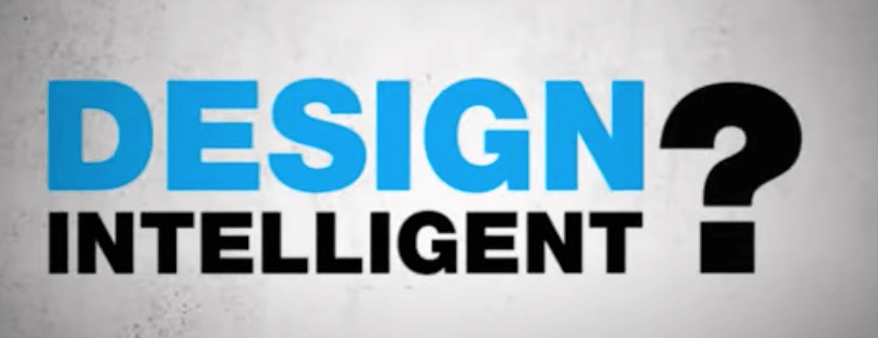
Dynamiser son design avec de la Typographie Animée
La Typographie : Place à l’animation et au Motion Design !
Voici le 4eme numéro de notre dossier sur la typographie, on commence à avoir vu en grande partie ce qui compose une police. Mais il nous reste maintenant à s'intéresser à son utilisation en animation, dans des clips, teasers, etc.
La Typographie en animation
On sait que la typographie fait partie intégrante de tout projet créatif qu’il soit un logotype, une affiche, un visuel, un site internet mais également une vidéo ou une animation. Dans cette article nous allons essayer de faire un tour rapide sur son utilisation dans les teasers, clips musicaux, sur les sites web, mais également dans des livres ! Commençons tout de suite avec ce qu’on peut appeler le Motion Typo que l’on voit depuis plus de 2 ans envahir les animations du web.
Le Motion Typo
En quelques mots je dirais que c’est l’art de créer une animation, avec comme seul élément principal "la typographie", ensuite c’est un jeu de mouvements, de compositions et de constructions avec les caractères. Voici quelques exemples pour illustrer.
La déclaration des droits de l’homme
Une animation reprenant la déclaration des droits de l’homme en vidéo conçue par Seth Brau et produit par Amy Poncher, on parcourt les différents plans entre illustrations et typographies sur une musique de Rumspringa.
Intelligent Design
Petite animation bien réalisée qui explique comment créer un design réfléchi et qui fonctionne, réalisé par Chrisitian Bramsiepe.
La typographie dans les Clips de musique !
Poursuivons notre dossier sur son utilisation dans les clips de musique, qui amène une dose de créativité et d’expérimentation pour le plus grand plaisir des yeux et des oreilles aussi ^^
Softlightes "Heart Made Of Sound"
Dans les teasers ou annonces d’évènements  !
Il parrait logique d’utiliser la typographie pour présenter des teasers où une grande partie de la vidéo, d’informer sur le sujet et de présenter l’évènement…Une petite liste d’exemples pour illustrer tout ça.
Join the Cannes Young Lions 48 Hour Ad Contest
La vidéo présente une compétition organisée en mai pour les Lions de Cannes, avec une animation fraiche et dynamique qui possède de très belles transitions, pour en savoir plus sur l’évènement rendez-vous sur la page officielle.
Pour compléter en bonus
On a pu voir différents domaines où l’on utilise la typographie, mais nous avons fait que survoler, car les créations sont tellement vastes qu’on ne pourrait pas toutes les regrouper. Voici 2 autres exemples qui montrent les possibilités en typo dans le Print avec un livre animé  et une création en grand format d’une police !
ABC 3D de Marion Bataille